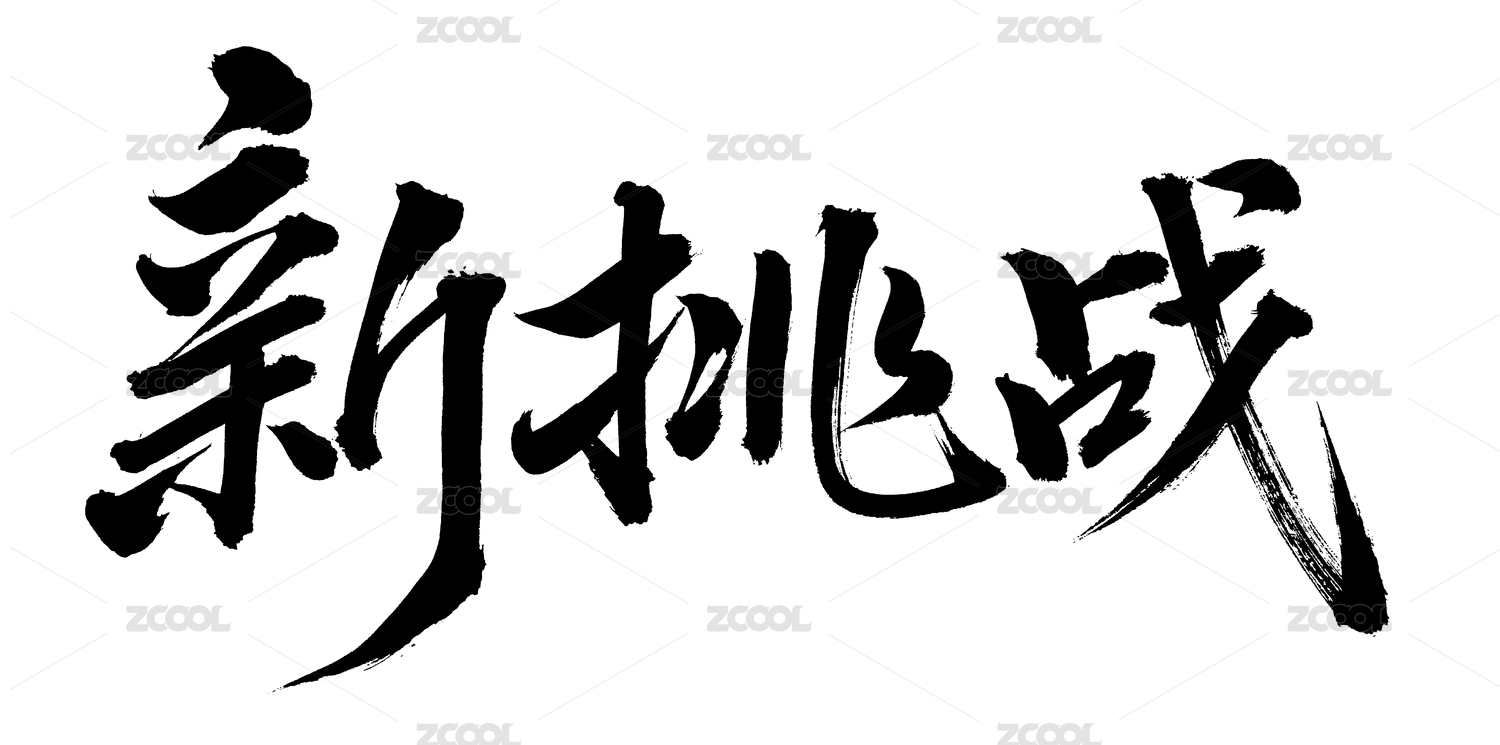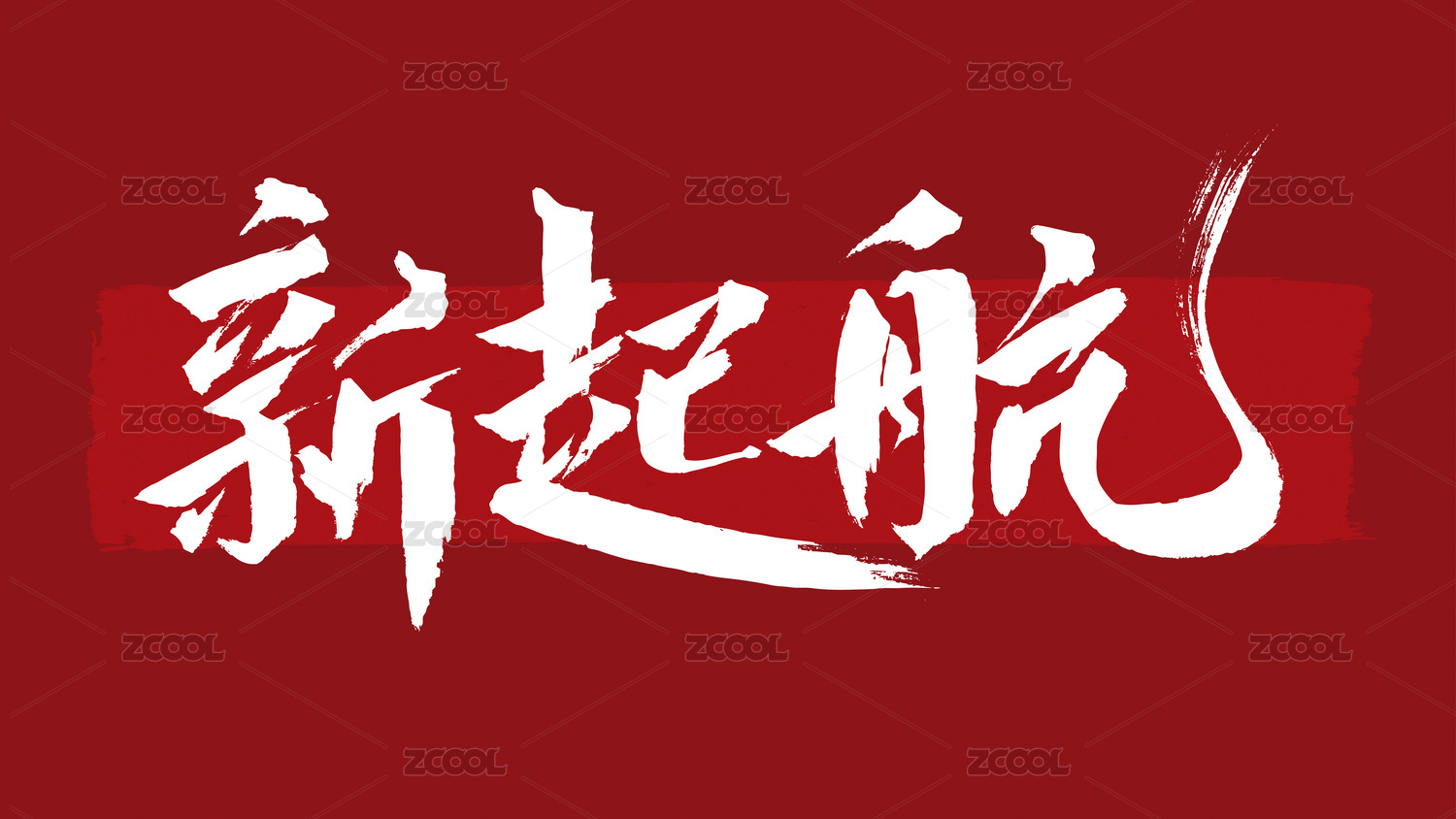
2010年的毕业作品
毕业两年了,看到站酷征集2012年的毕业设计,就想到我毕业时的作品了。
学的是国画,毕业创作选的是书法,当时真实的想法是图个省事,完成的快,还不要写论文,哈哈。。。
十个斗方组成的一个长卷,元素毛边纸,整幅太长,家里都挂不下。失踪了一年多,上周无意被我翻出来了,是我妈给藏起来的,就怕被家里的亲戚朋友看到后给顺走。
水平不高,被导师批多夸少,什么字与字之间断气啊,下不对齐啊,简繁混杂啊,个别字写法不对啊之类的。外行人看着还像那么回事,内行人就要摇头了。
总之,书法我不专业,只是个爱好,坚持就好。